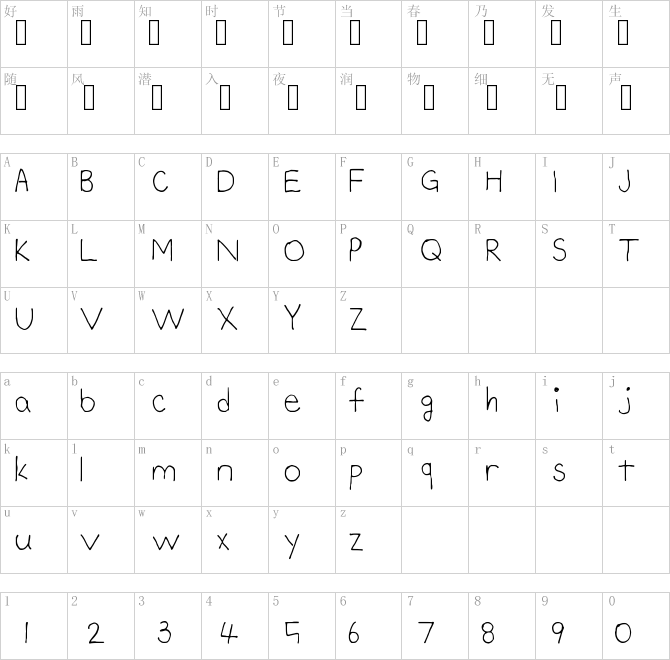
나눔손글씨 따뜻한 작별韩国字体
나눔손글씨 따뜻한 작별韩国字体,这款字体结构工整、笔画清晰,兼顾美观与易读性,适用于标题、正文、海报、包装、LOGO 等多种场景。字形优雅稳定,风格百搭耐看,适配日常排版与创意设计,让文字呈现更舒适、更具质感。나눔손글씨 따뜻한 작별韩国字体一笔一画,皆是细节,以均衡的比例、流畅的线条打造舒适视觉体验,字形端正大气,风格简约现代。无论是商业设计、品牌宣传还是日常排版,都能轻松驾驭,让文字更有格调与力量。나눔손글씨 따뜻한 작별韩国字体字体下载。